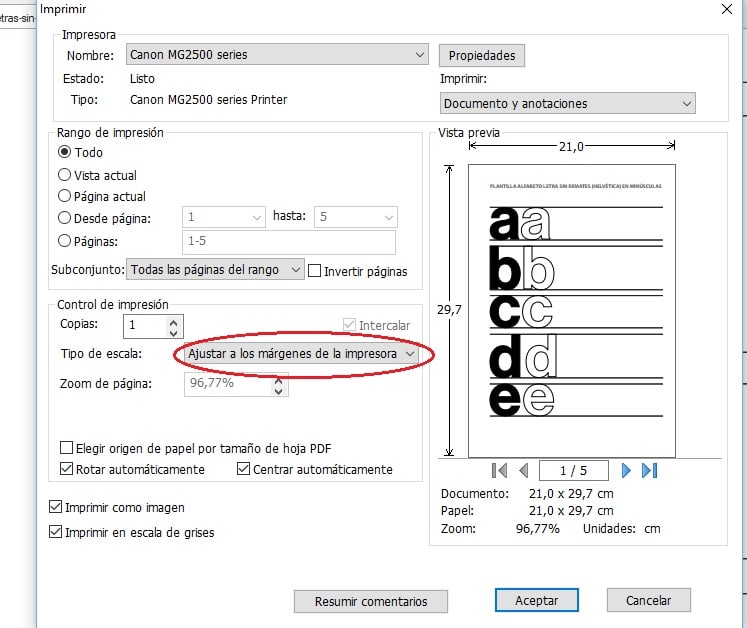
Aquí os traemos una plantilla de lettering de letra sin remates, concretamente, la Helvética. Si queréis saber más sobre este alfabeto, os recomendamos que visitéis nuestro post: Alfabeto letra sin remates: Helvética en mayúsculas y minúsculas, en donde os explicamos algunos de sus usos y sus características principales a la hora de dibujarlas.
Cuando esté impresa, podéis proceder a copiarla al lado para familiarizaros con este tipo de alfabeto. Os sugerimos utilizar un papel de 90gr/m2 de tamaño A4 para que los resultados sean mejores.
Como siempre, os recomendamos que no copiéis dibujando los contornos, sino que identifiquéis los bloques que componen cada letra, la dibujéis por bloques y, luego, ya haréis los acabados y las modificaciones pertinentes para personalizar vuestro lettering con letra sin remates. Es una letra muy geométrica, así que tanto la podéis dibujar a mano alzada como utilizando reglas rectas para los bloques rectos o reglas curvas o plantillas de elipses para las partes curvas de la letra. Todo es cuestión de práctica y de perfeccionamiento a la hora de dibujar las formas lo más perfectas posibles.